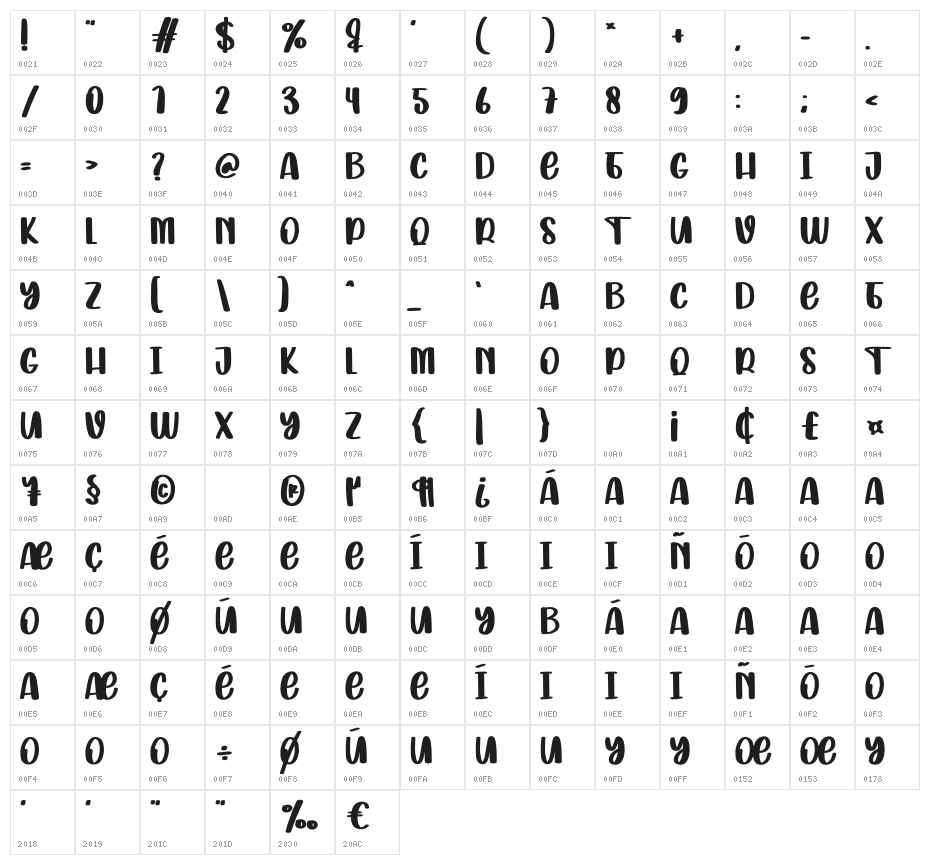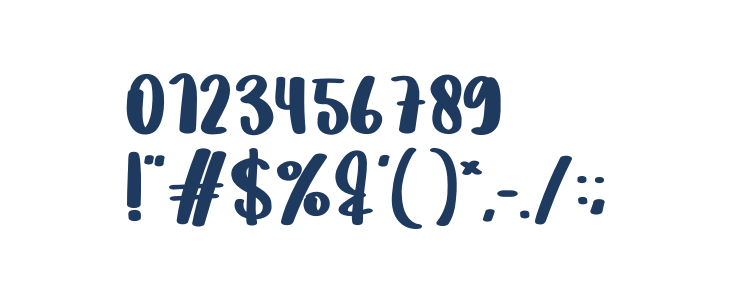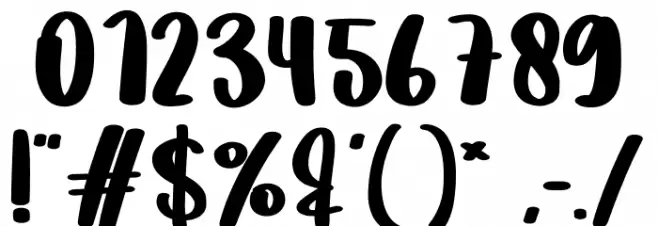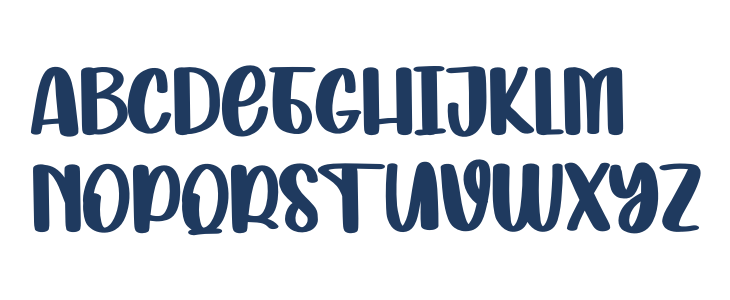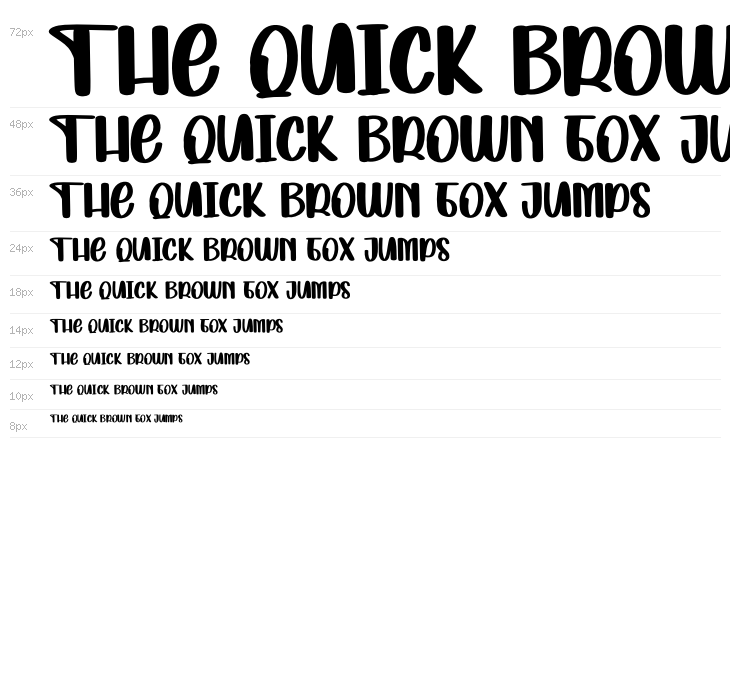
Snow Holiday Font
| Gesamtstil | Playful, Decorative, Casual |
| Anwendungsfall | Headlines, Logos, Posters, Invitations |
| Vorgeschlagene Projekte | Greeting cards, holiday invitations, children's books, playful branding, posters, social media graphics. |